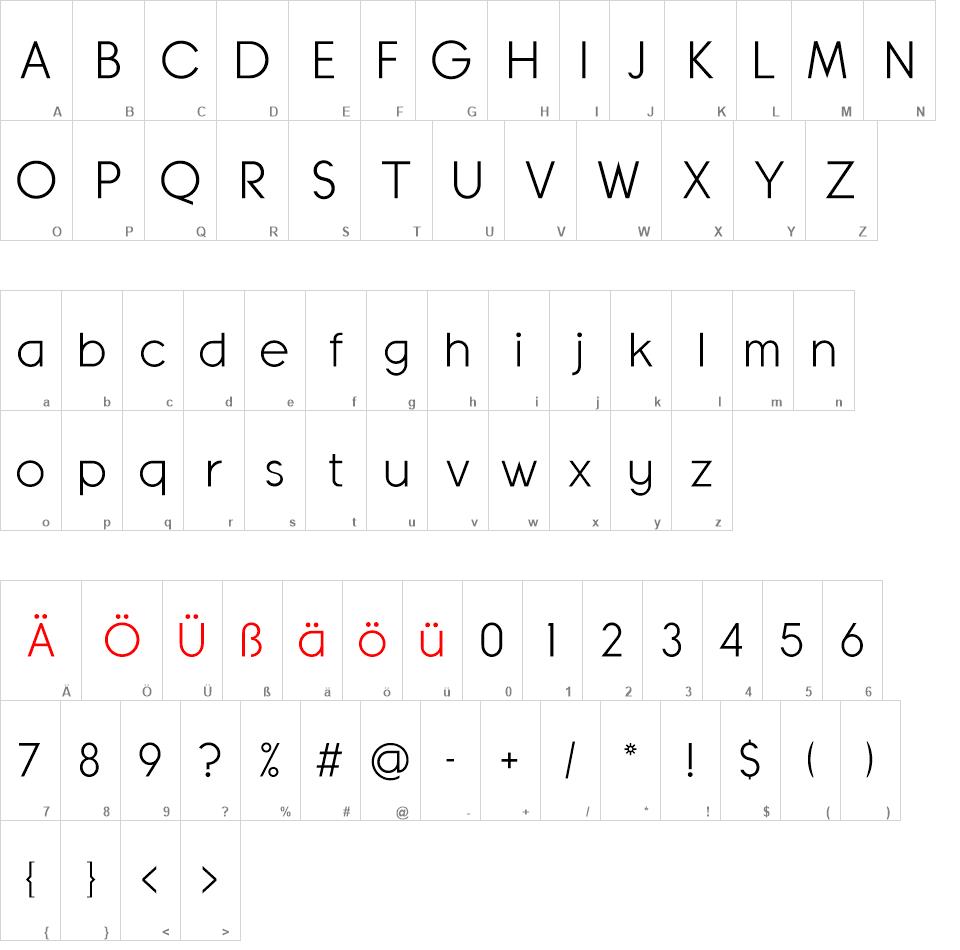
Banks Miles
Banks Miles  font
Banks Miles
Die Banks & Miles-Schriftarten von K-Type sind inspiriert von dem geometrischen Monoline-Schriftzug, den die Londoner Designfirma Banks & Miles 1970 für das britische Postamt entworfen hatte und der "Double Line" - und "Single Line" -Alphabete enthielt.